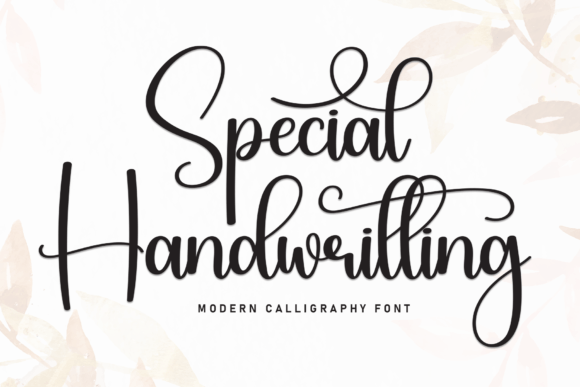
Special Handwritting
適切なデザイン要素を見つけるのは難しい場合がありますが、Special Handwrittingは作品を即座に引き立てる優れたコレクションを提供します。
POD(オンデマンド印刷)製品、結婚式の招待状、またはソーシャルメディアのグラフィックを作成している場合でも、Special Handwrittingは理想的です。